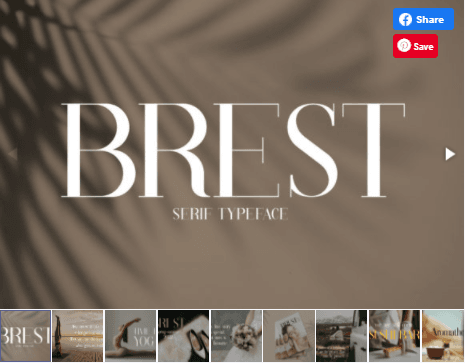
Brest Font
Brest - роскошный и элегантный шрифт с засечками. Его естественный и уникальный стиль делает его невероятно подходящим для большого количества дизайнерских решений. Единственным ограничением является ваше воображение!